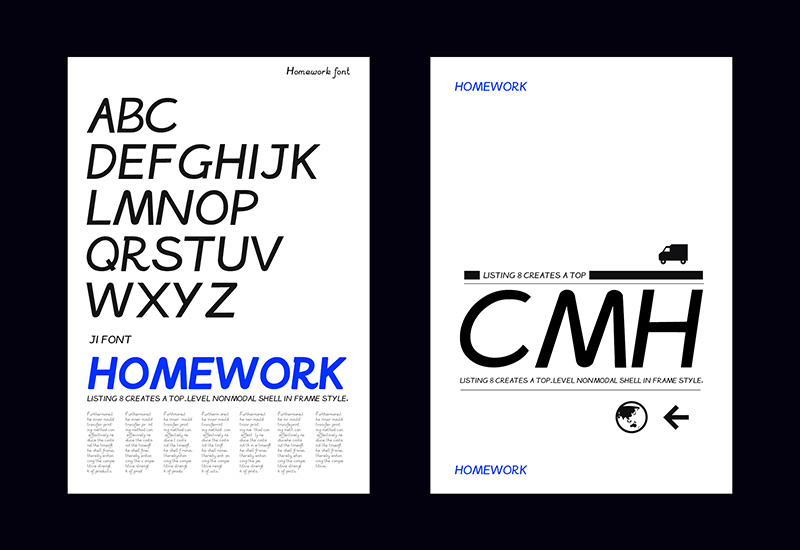
我在做完字體framework後,身邊不少朋友嫌棄使用場景太少,不實用(小聲嗶嗶:那是你不會用,hhh);我怎麼能忍受這種不負責的話呢,所以我不僅改良了framework還又做了一套字體homework,靈感嘛來源於小時候作業本上的英文單詞和句子,還記得那首“拼音字母歌”,“abcdefg hejklmn opq rst uvw xyz”旋律依舊熟悉難忘。